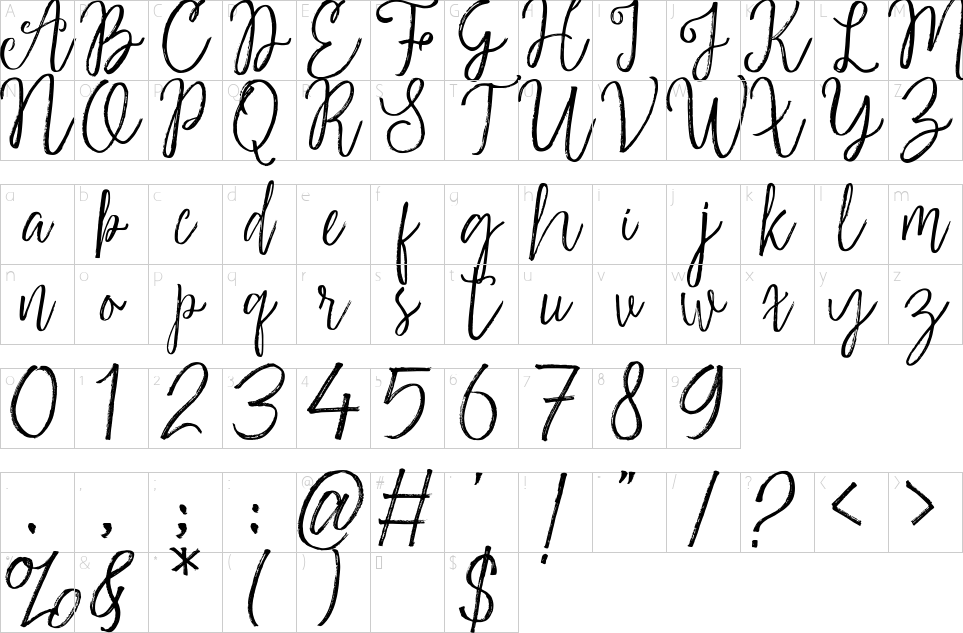
A fonte Misyela Script é uma escolha ideal para quem busca uma fonte de efeito gráfico elegante e sofisticada. Desenvolvida pela Stripes Studio, ela oferece um toque de elegância e personalidade em qualquer projeto, seja em logotipos, materiais de marketing, editoriais ou qualquer outro projeto que requer uma fonte de efeito. Com seus traços delicados e elegantes, a Misyela Script criará uma experiência visual agradável que destaca sua mensagem. Esta fonte é perfeita para designers e profissionais que procuram uma fonte de efeito para destacar suas criações. Recentemente, ela foi baixada 998 vezes, demonstrando o seu valor e popularidade entre os criadores de conteúdo. Se você está procurando uma fonte de efeito para seu próximo projeto, a Misyela Script é uma ótima escolha.